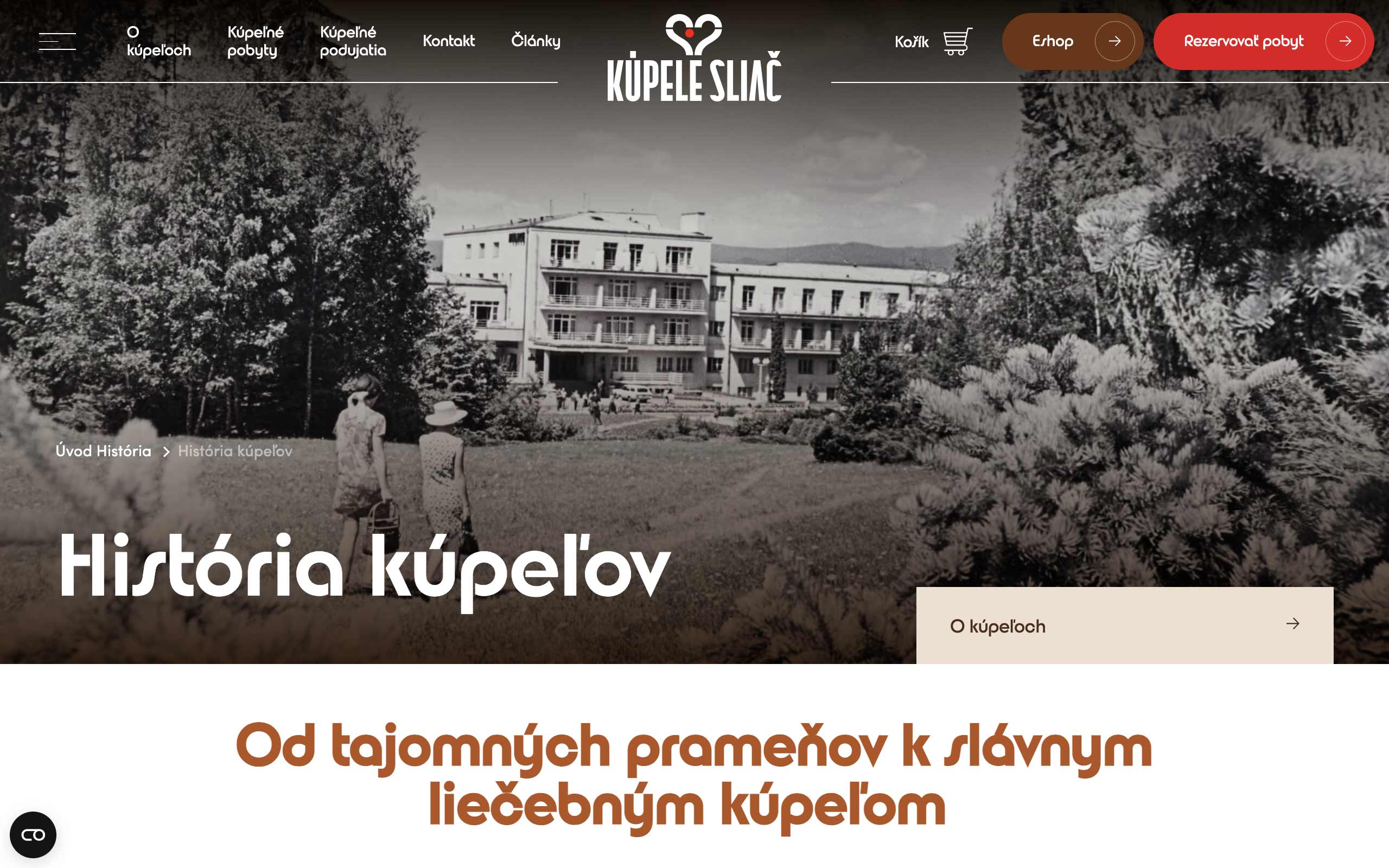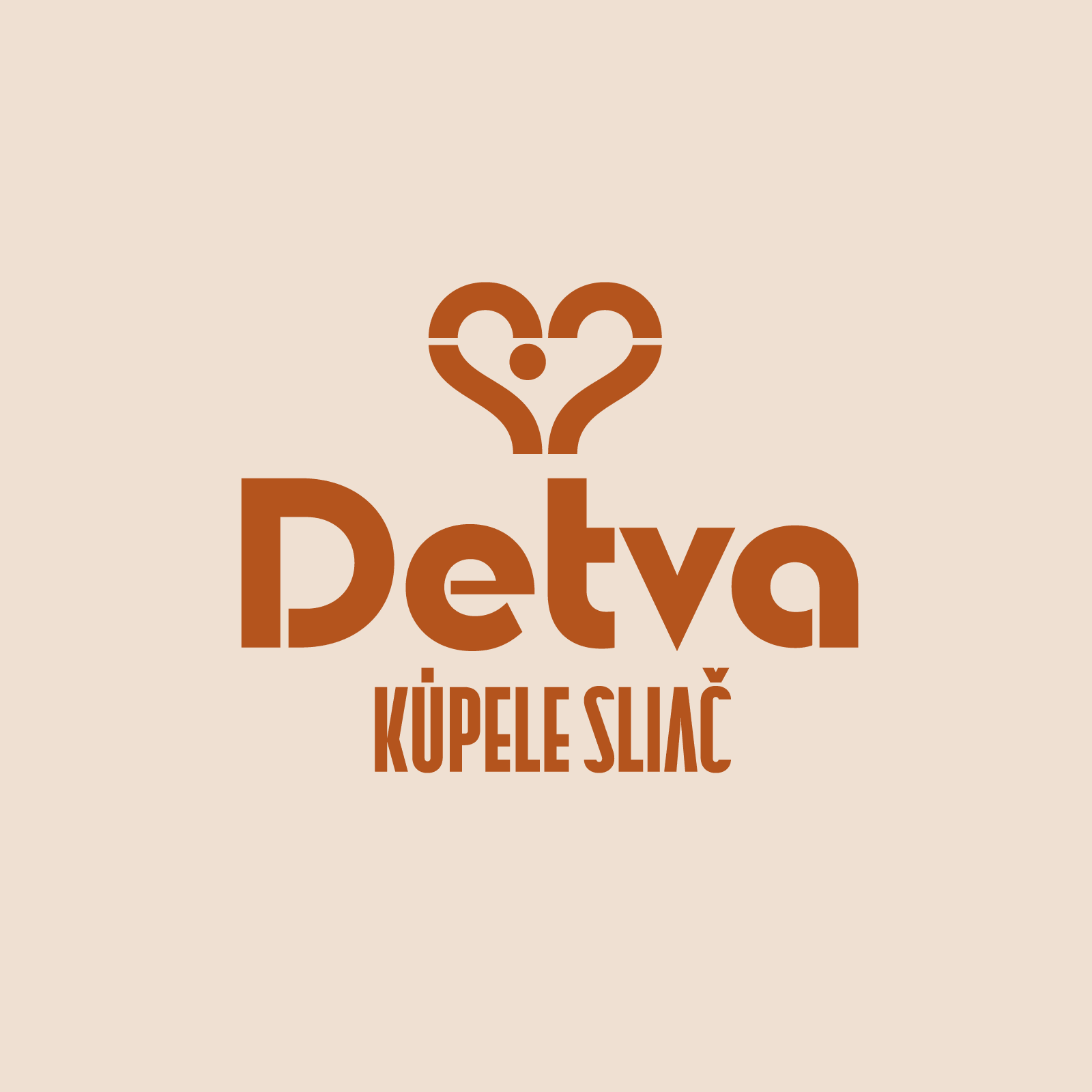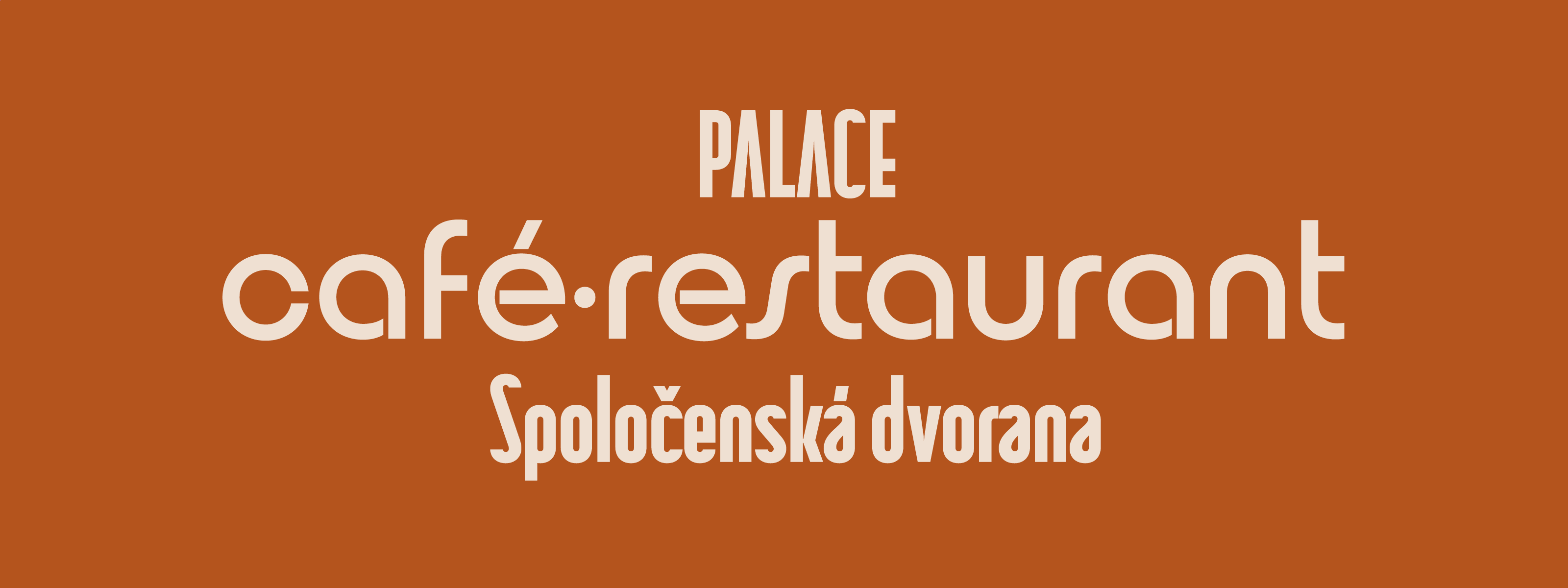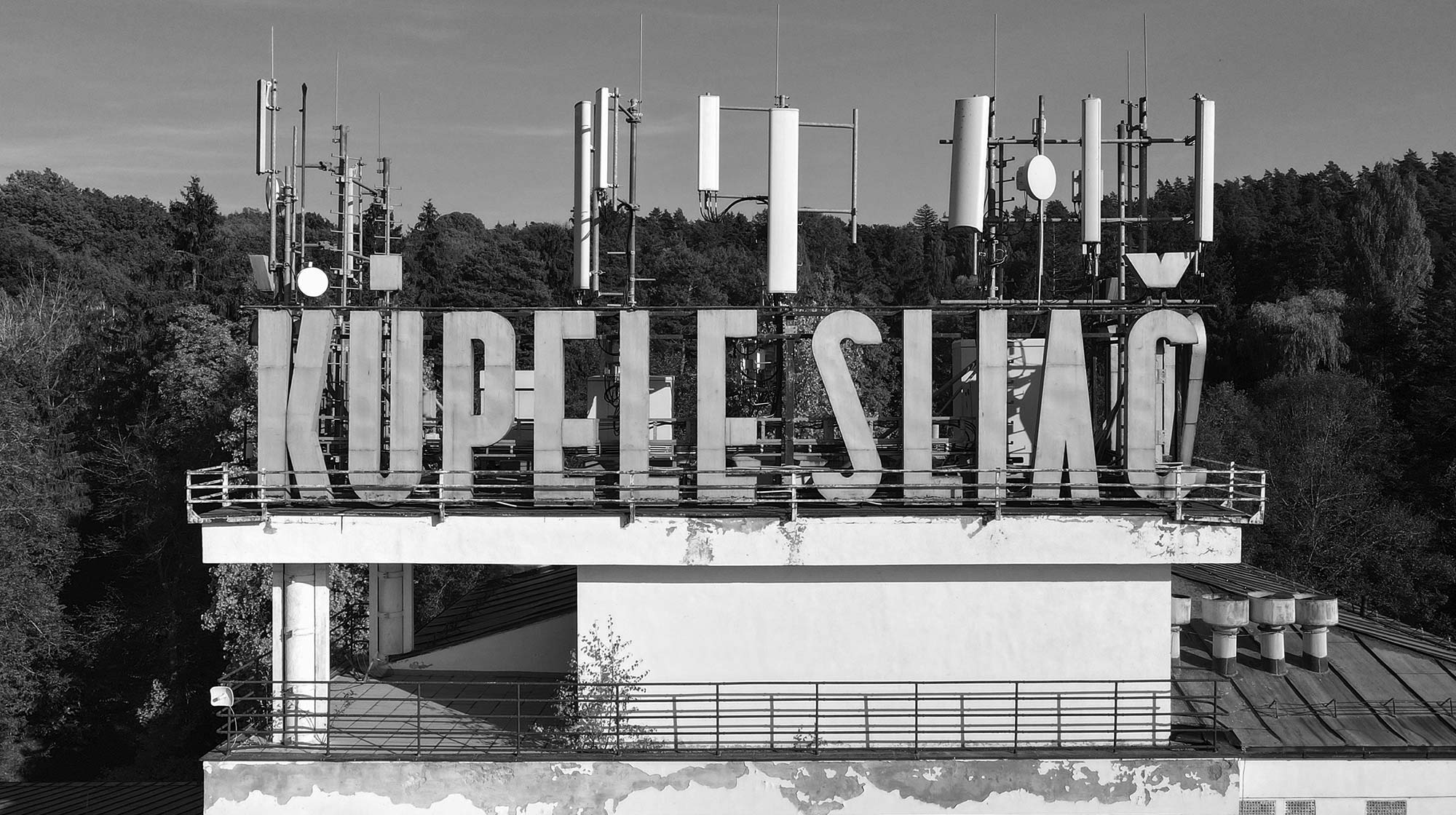
Kúpele Sliač
Dvojica písiem vytvorených na mieru pre Kúpele Sliač.
Nové písma sú digitalizáciou dvoch písiem používaných na značenie v areáli kúpeľov. Prvé písmo je pôvodné písmo navrhnuté architektom Rudolfom Stockarom v roku 1924 špeciálne pre nový kúpeľný komplex, v súčasnosti zachované už len v nápise na streche kúpeľného hotela Palace. Druhé písmo, dodnes používané vo forme svietiacich nápisov na označenie prevádzok v rámci kúpeľného areálu, bolo existujúce písmo zavedené do používania v 70. rokoch 20. storočia (podľa predpokladu).